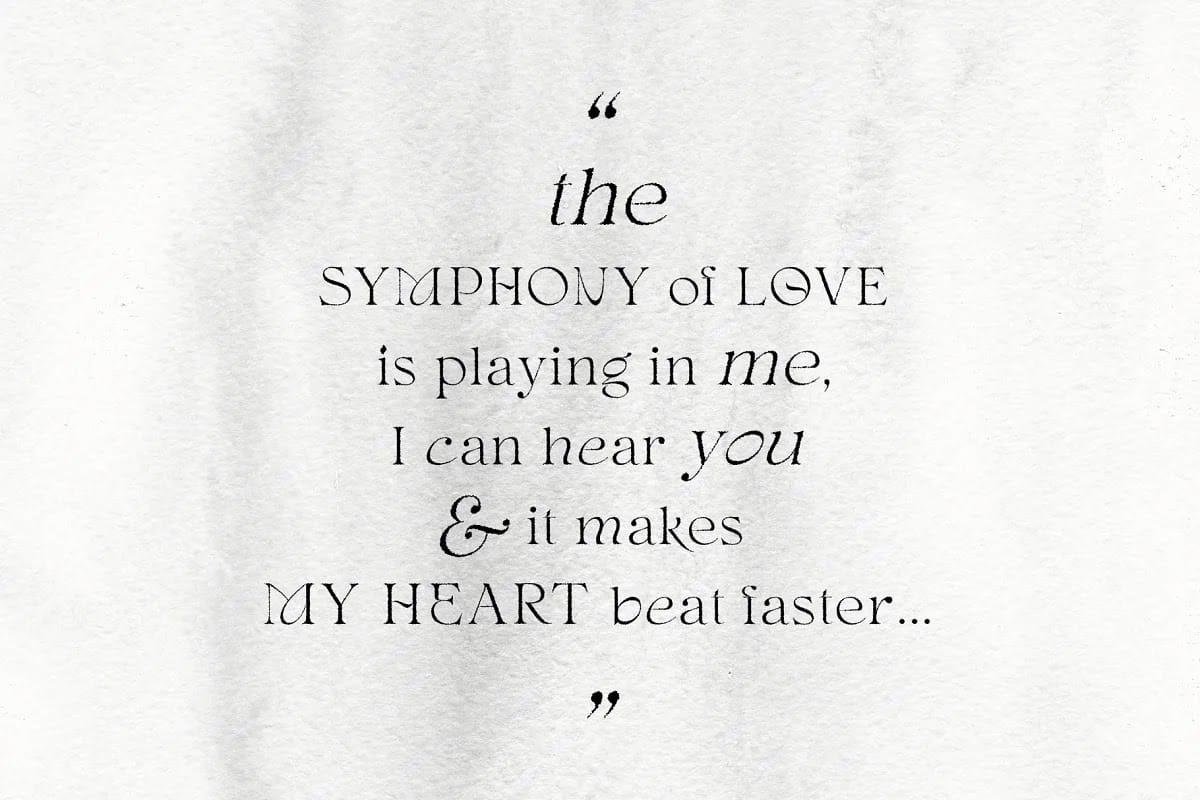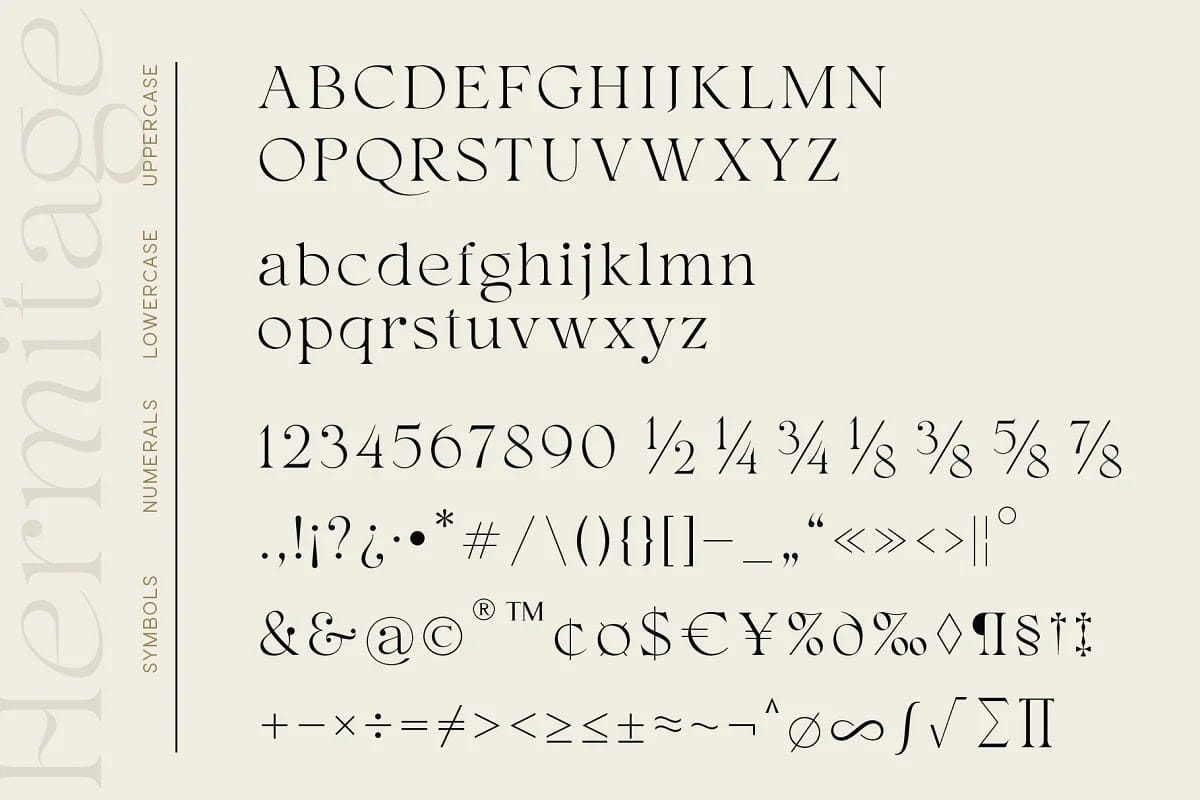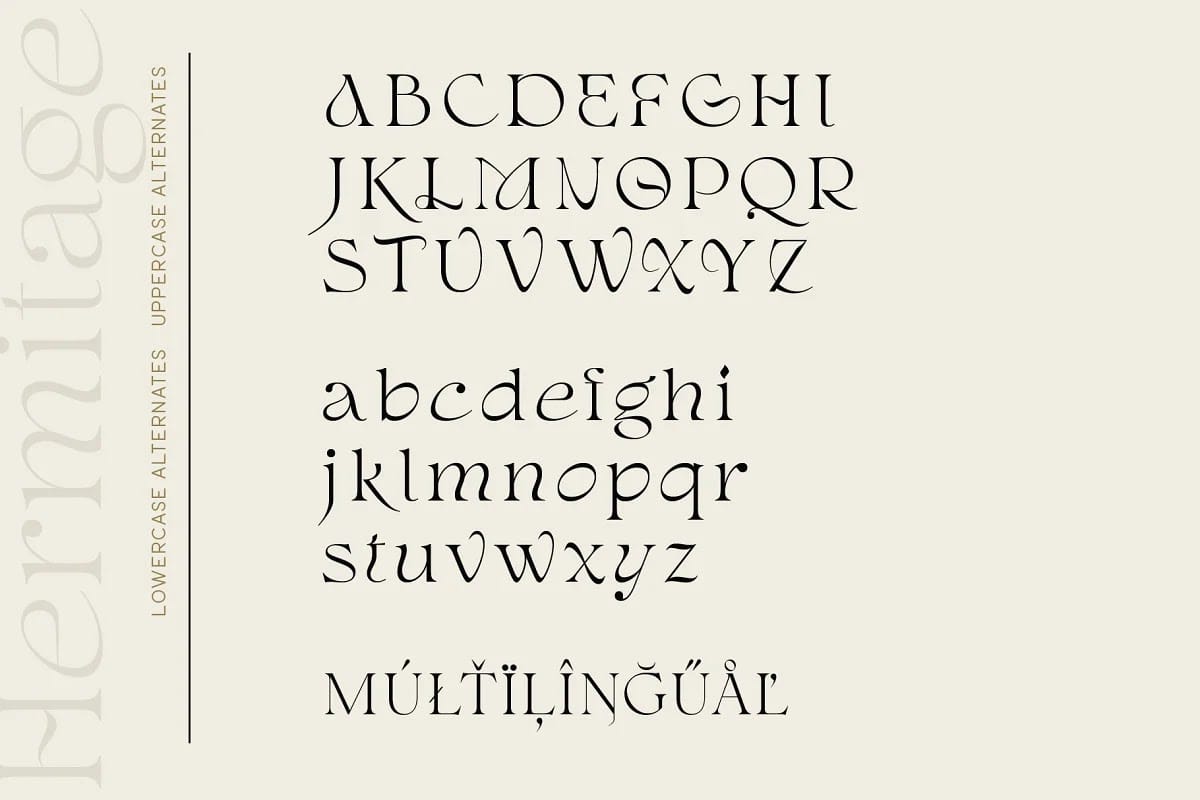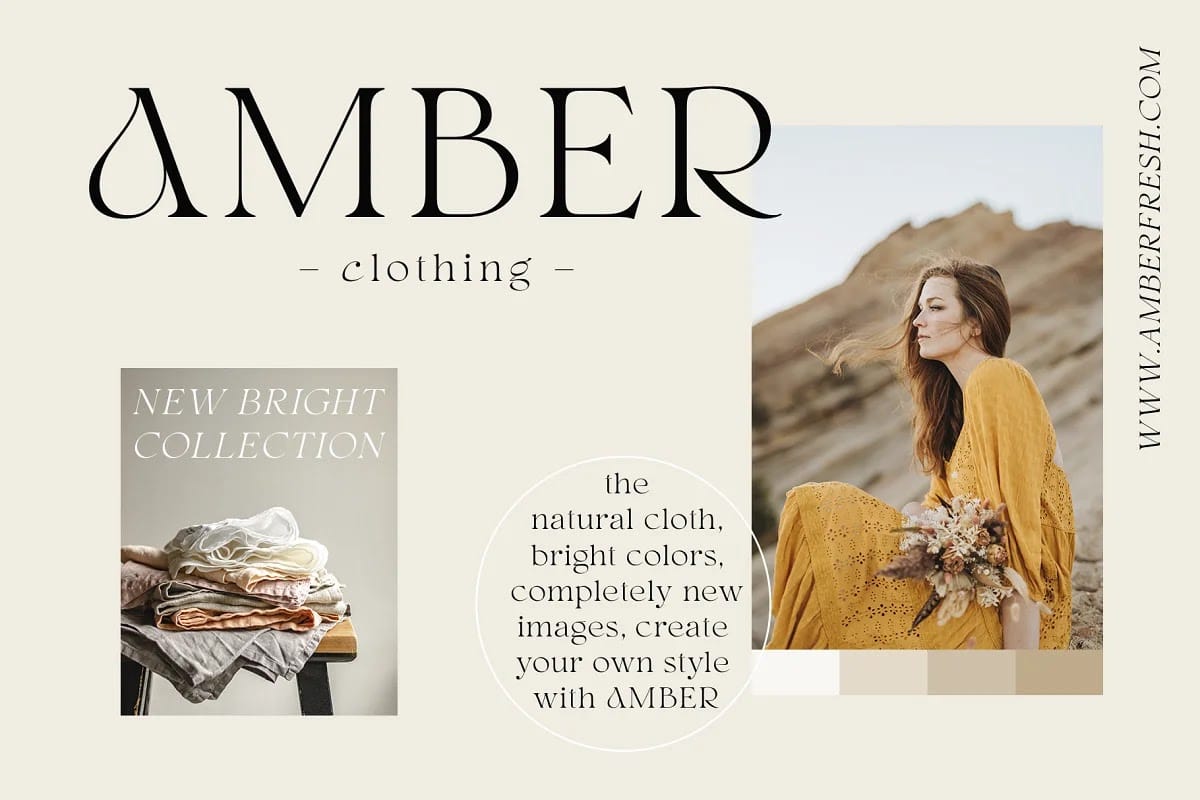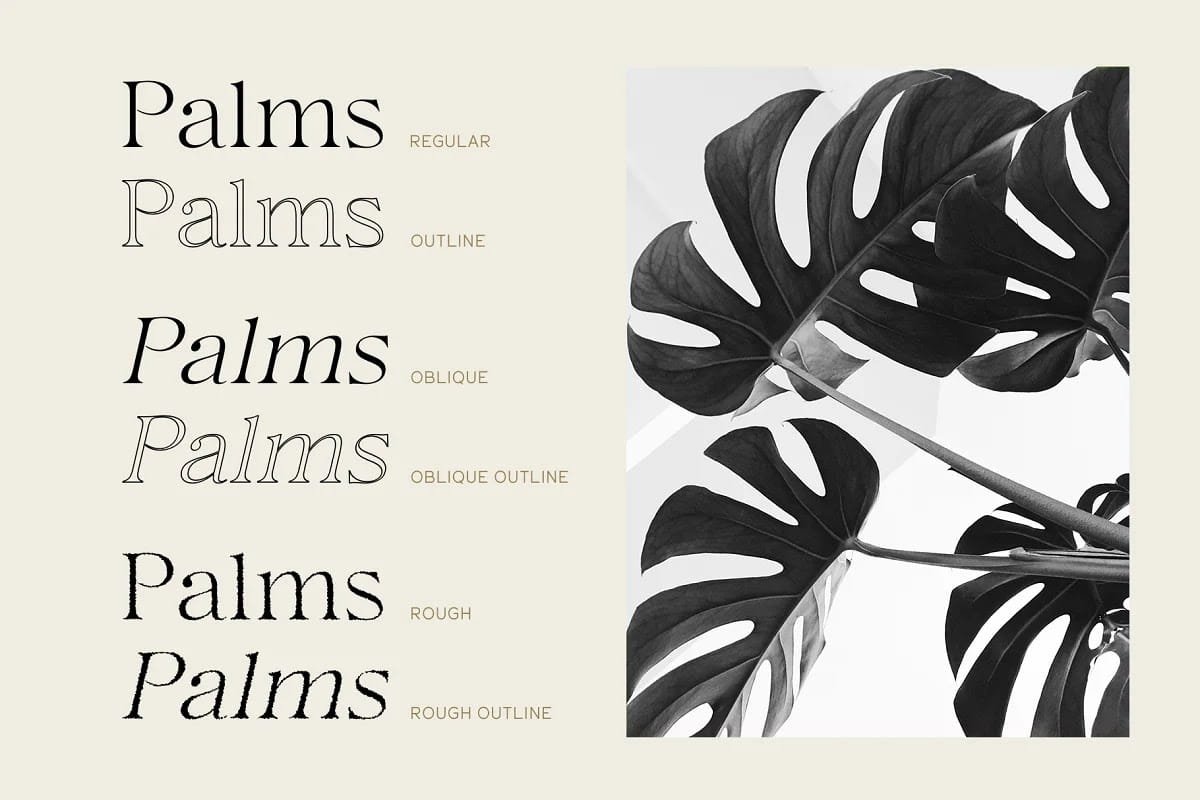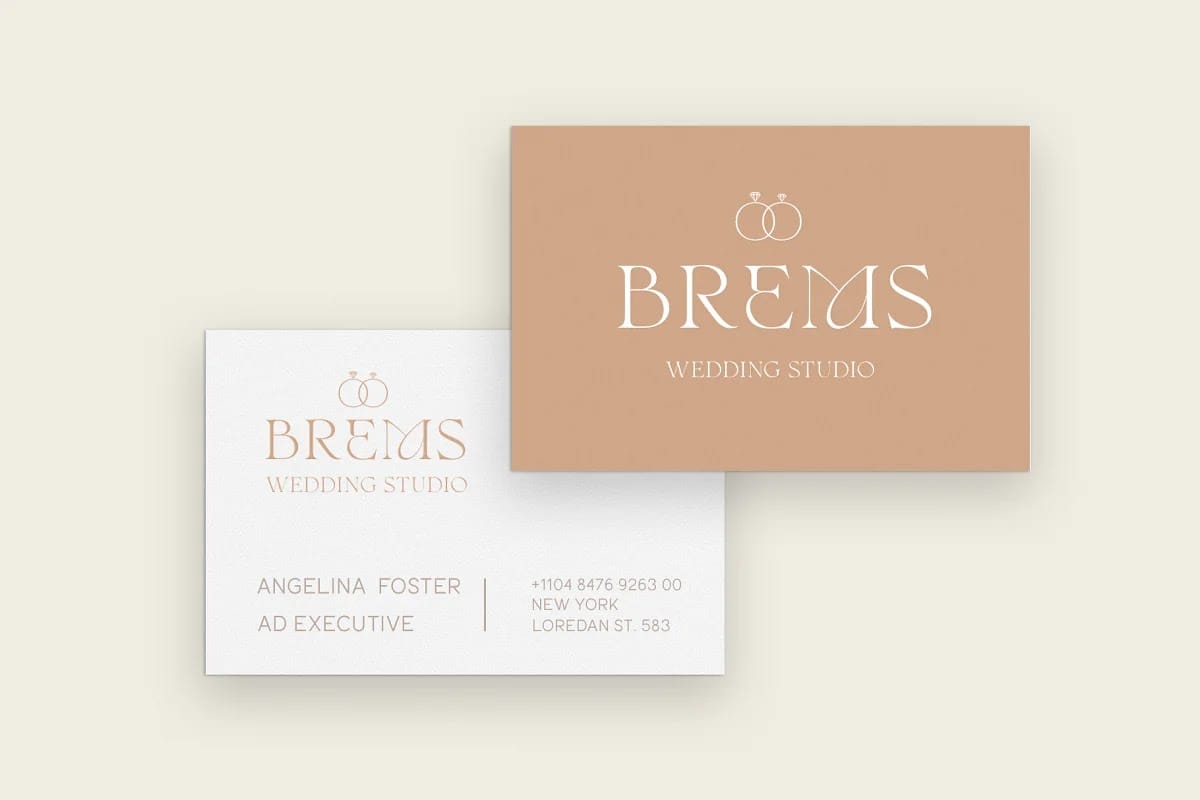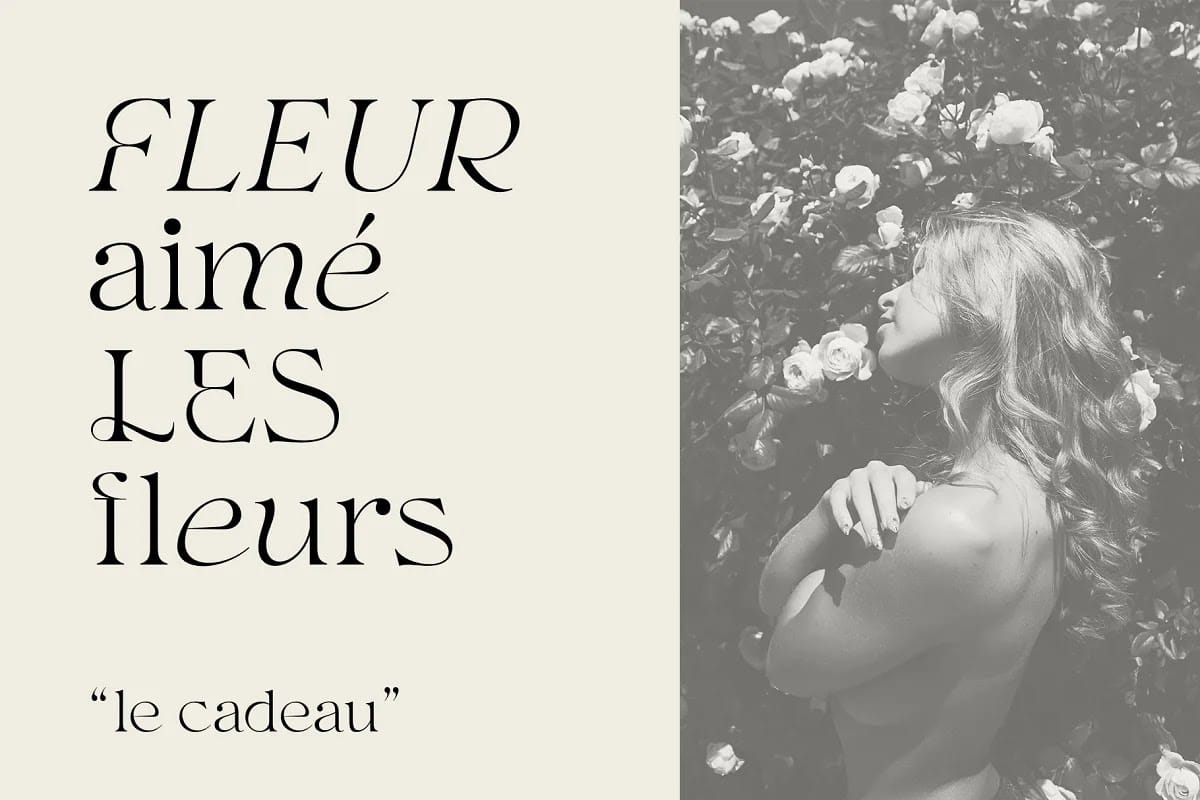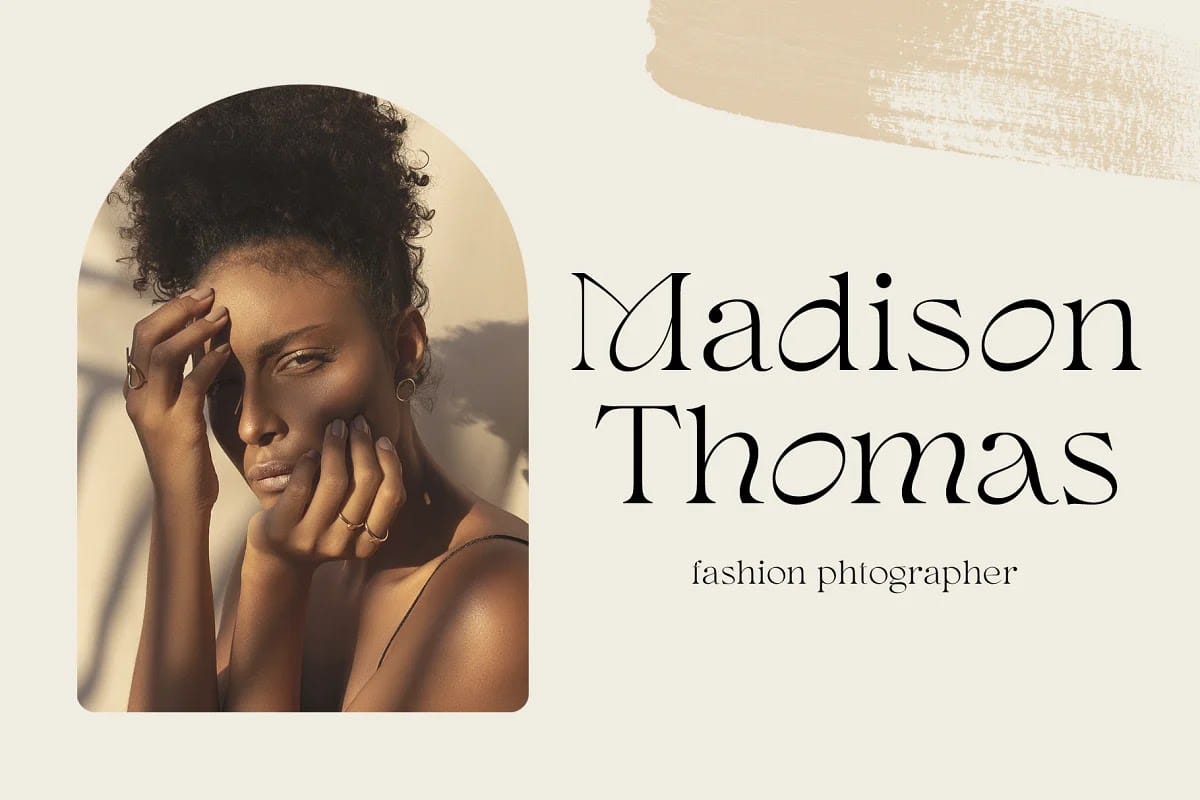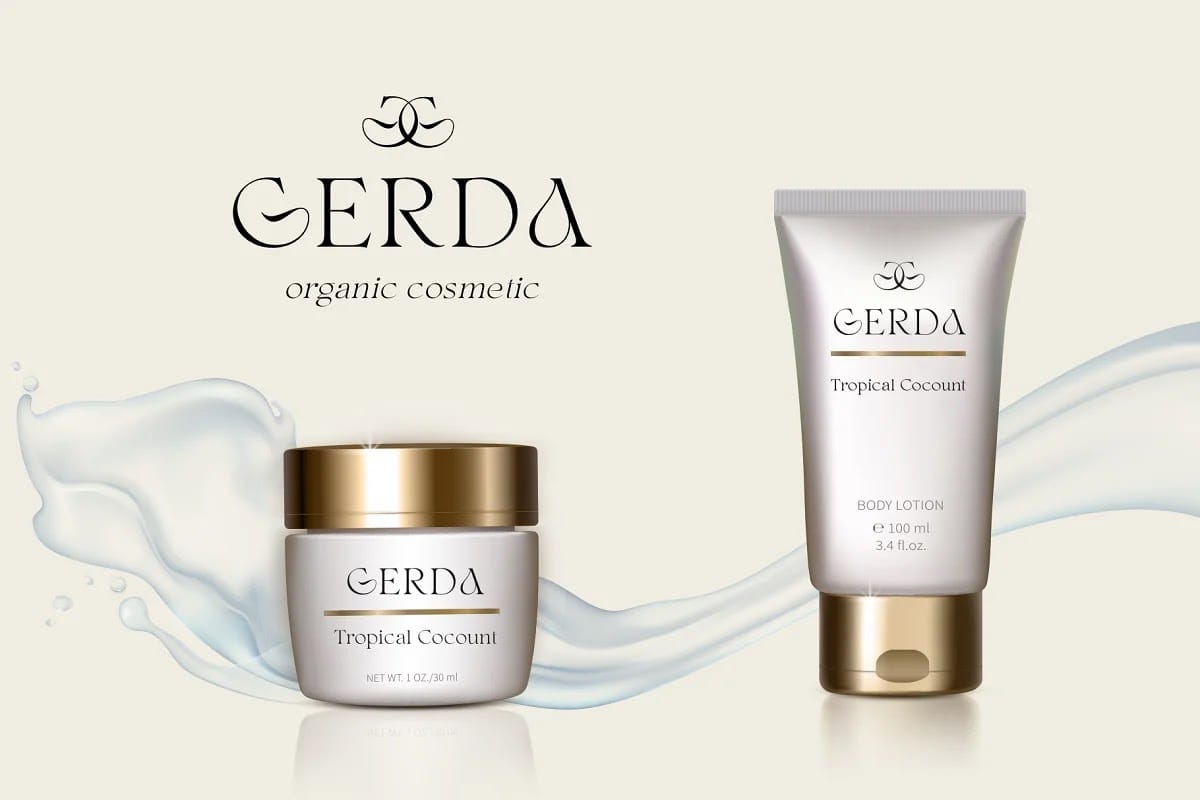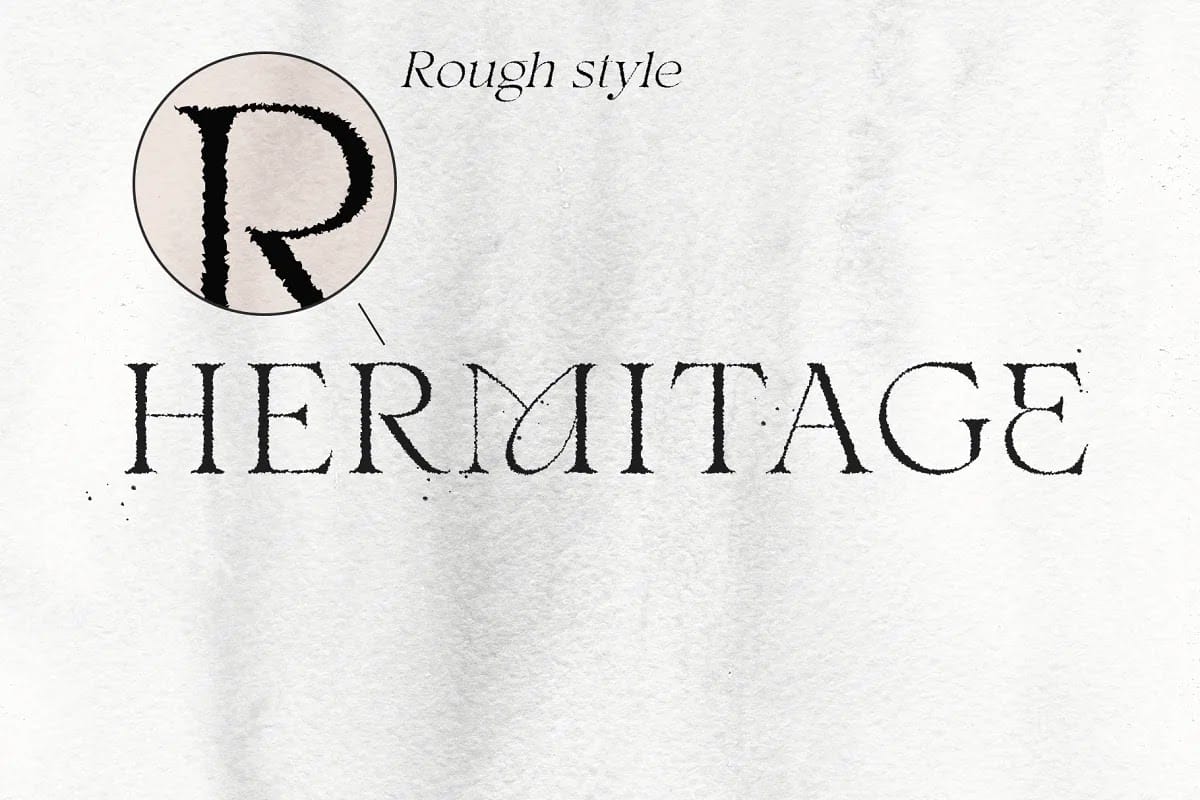
Hermitage Font Family (6 Font) – Độc đáo, thanh lịch
Hermitage là một font chữ serif hiện đại, thanh lịch bao gồm 6 kiểu chữ regular, outline, oblique, outline oblique, rough và rough oblique.Font chữ này có một thiết kế ấn tượng và trông tuyệt vời để thiết kế thương hiệu, sắp xếp lời mời đám cưới, danh thiếp, bao bì, mỹ phẩm, cũng hoạt động hoàn hảo với văn bản, nó rất dễ đọc và dễ nhận biết, bìa sách, tiêu đề tạp chí hoặc đơn giản là một văn bản phong cách lớp phủ lên bất kỳ hình nền nào. Font chữ này bao gồm các kiểu thay thế cho Chữ hoa và Chữ thường, với chúng, bạn có thể làm cho dự án của mình thanh lịch và độc đáo hơn và kiểu chữ nghiêng sẽ thêm động lực cho thiết kế của bạn. Sử dụng một phong cách thô trên giấy thủ công, nó sẽ trông tuyệt vời trên đó và tạo ra một thiết kế ấn tượng của chữ viết tay. Font chữ này dễ sử dụng có các tính năng OpenType.